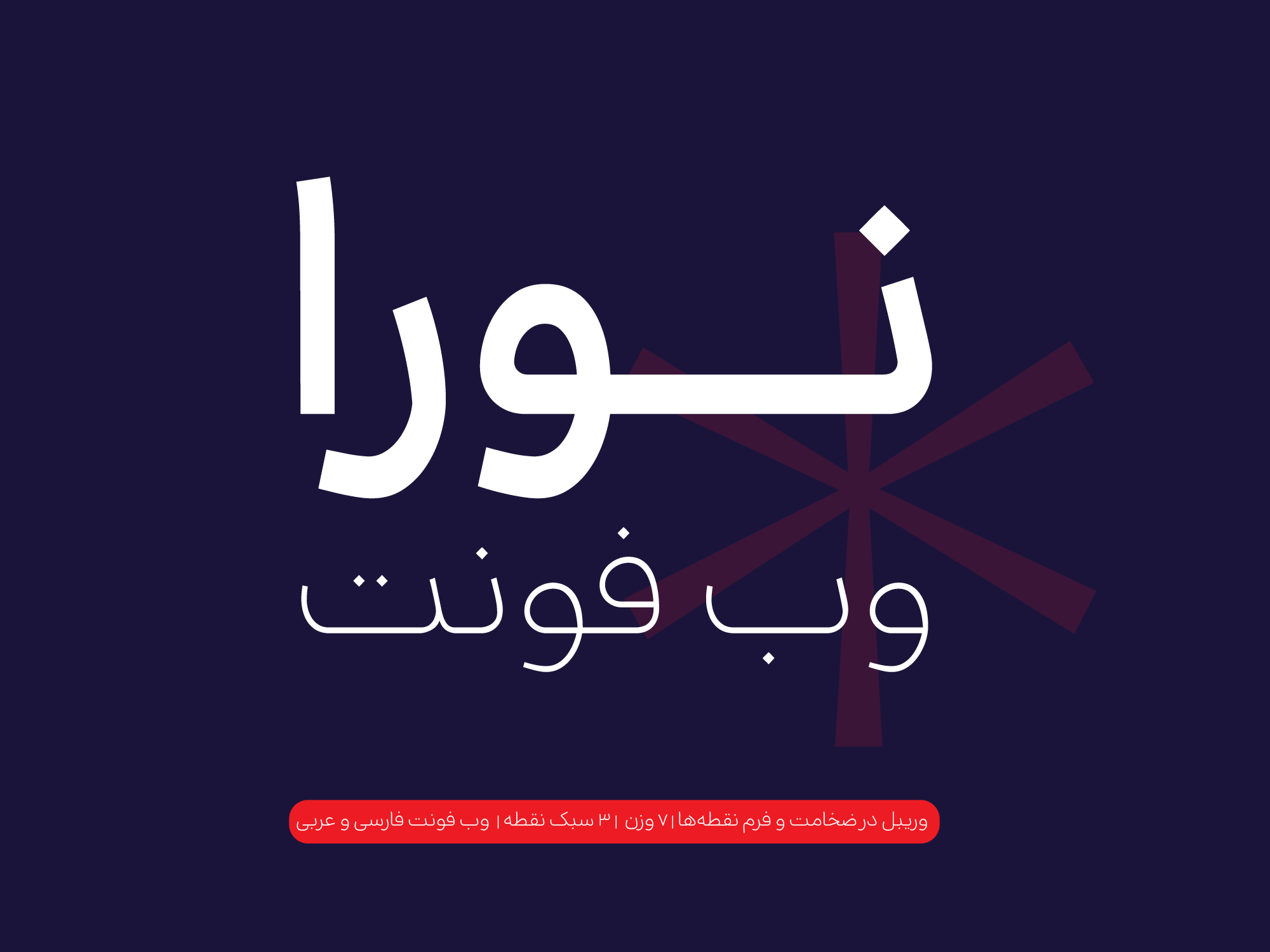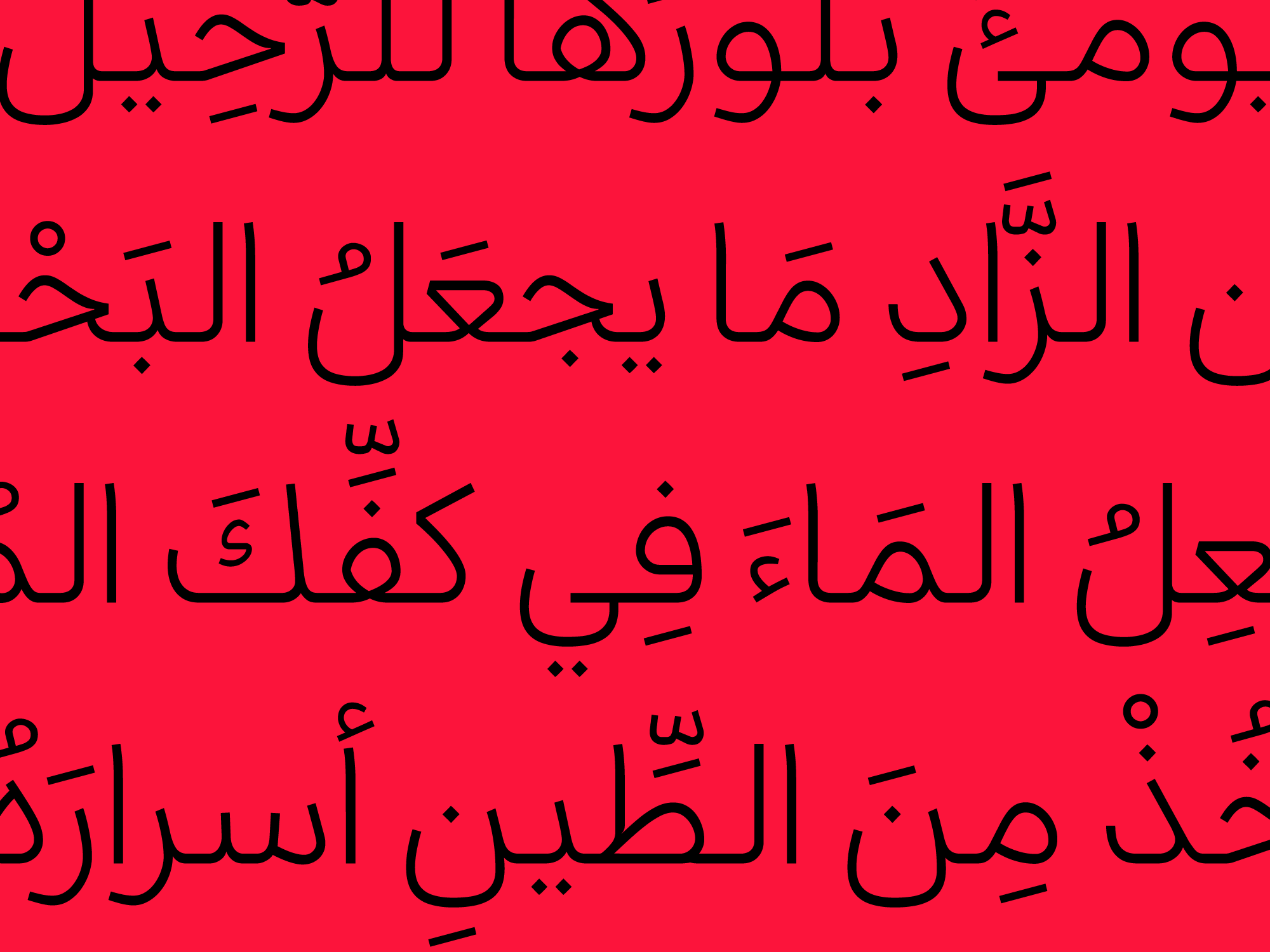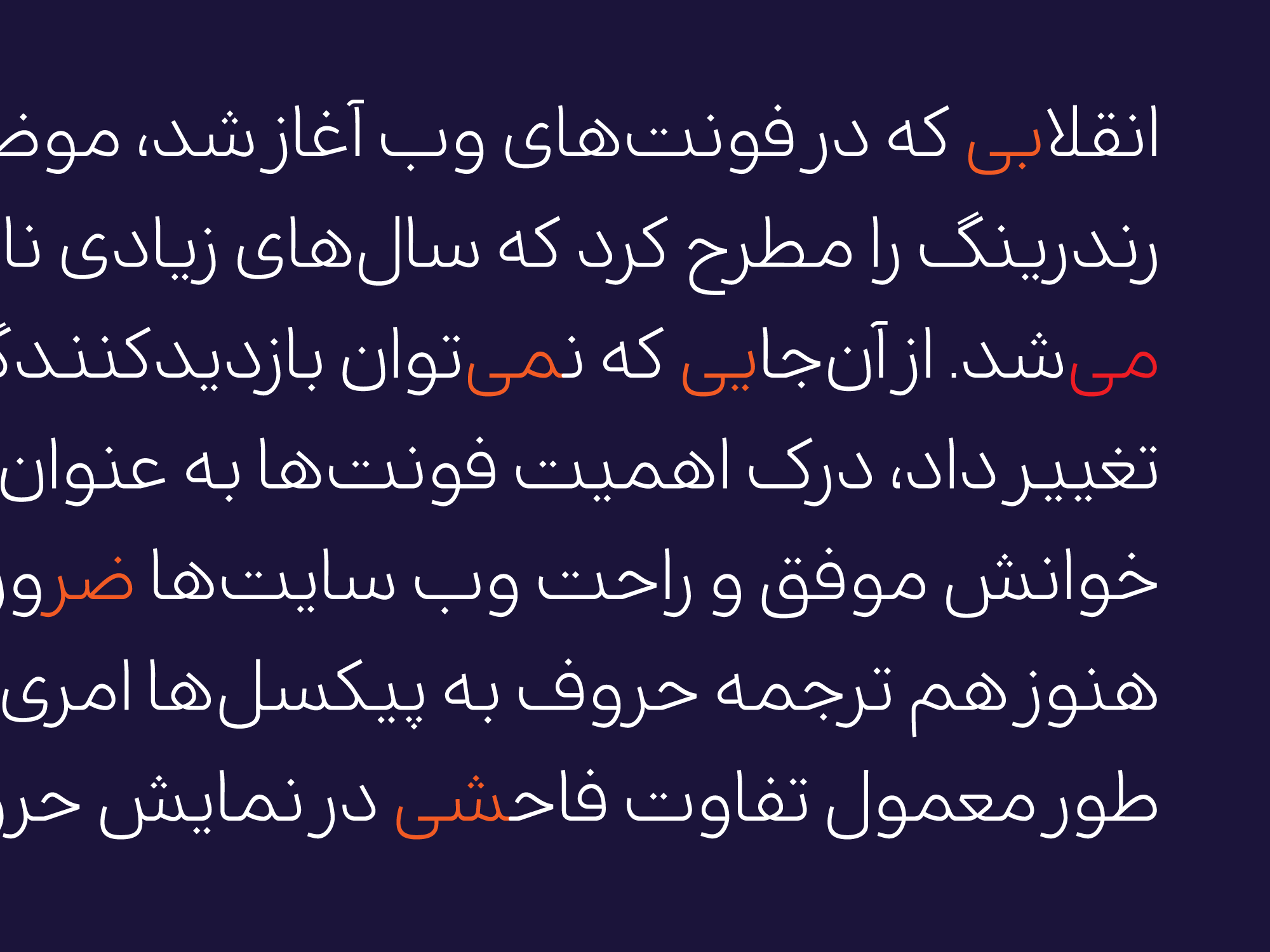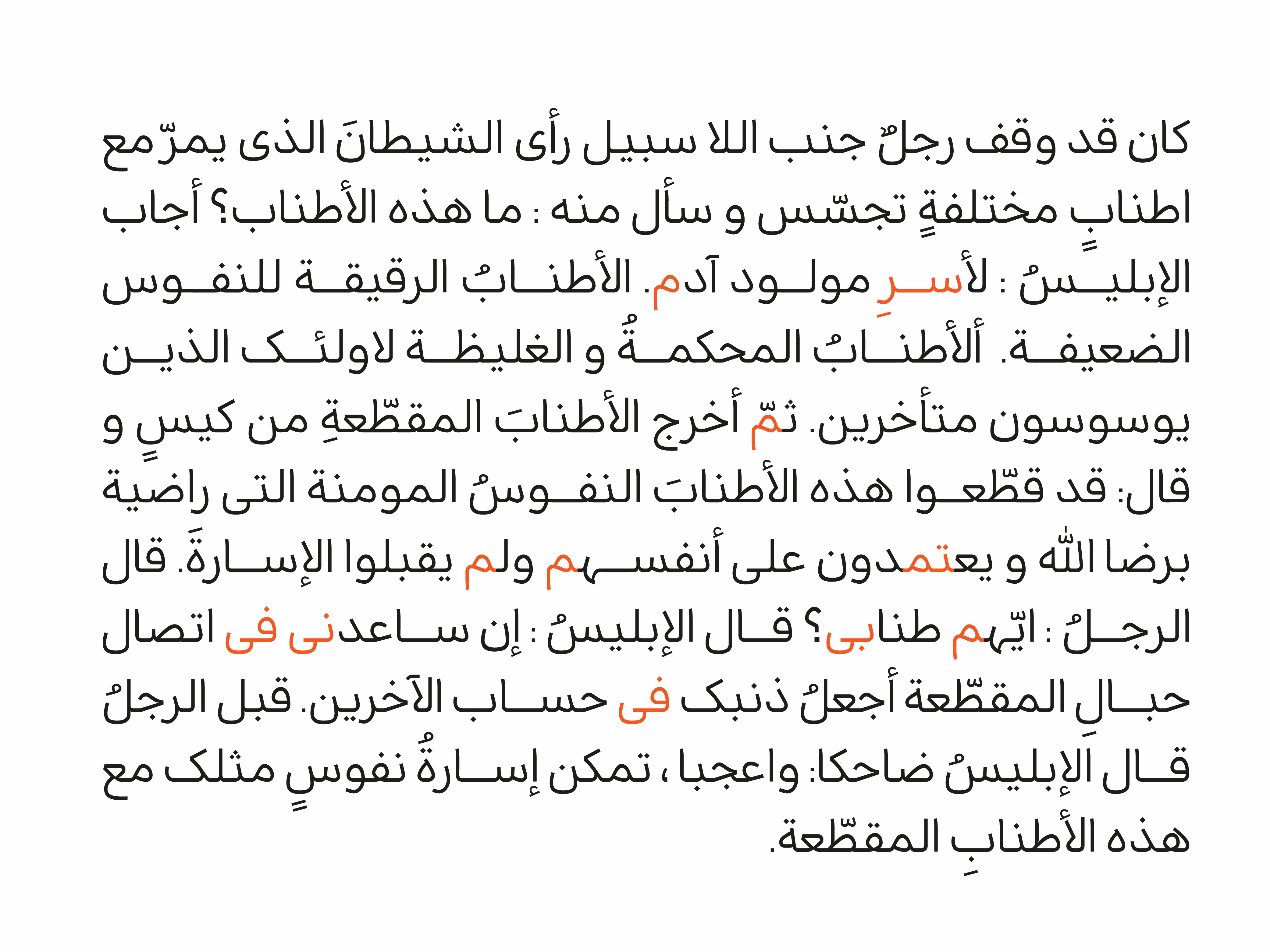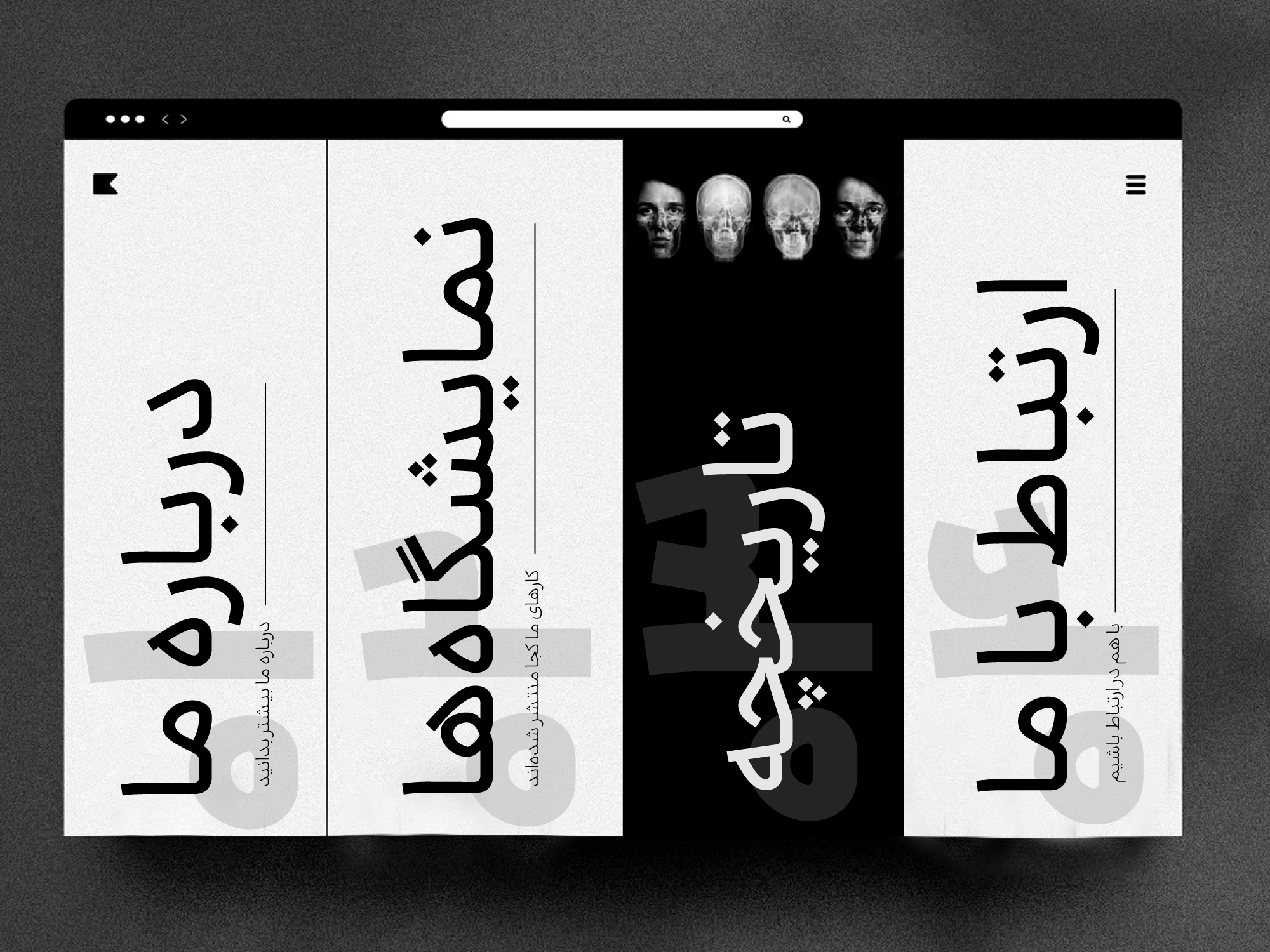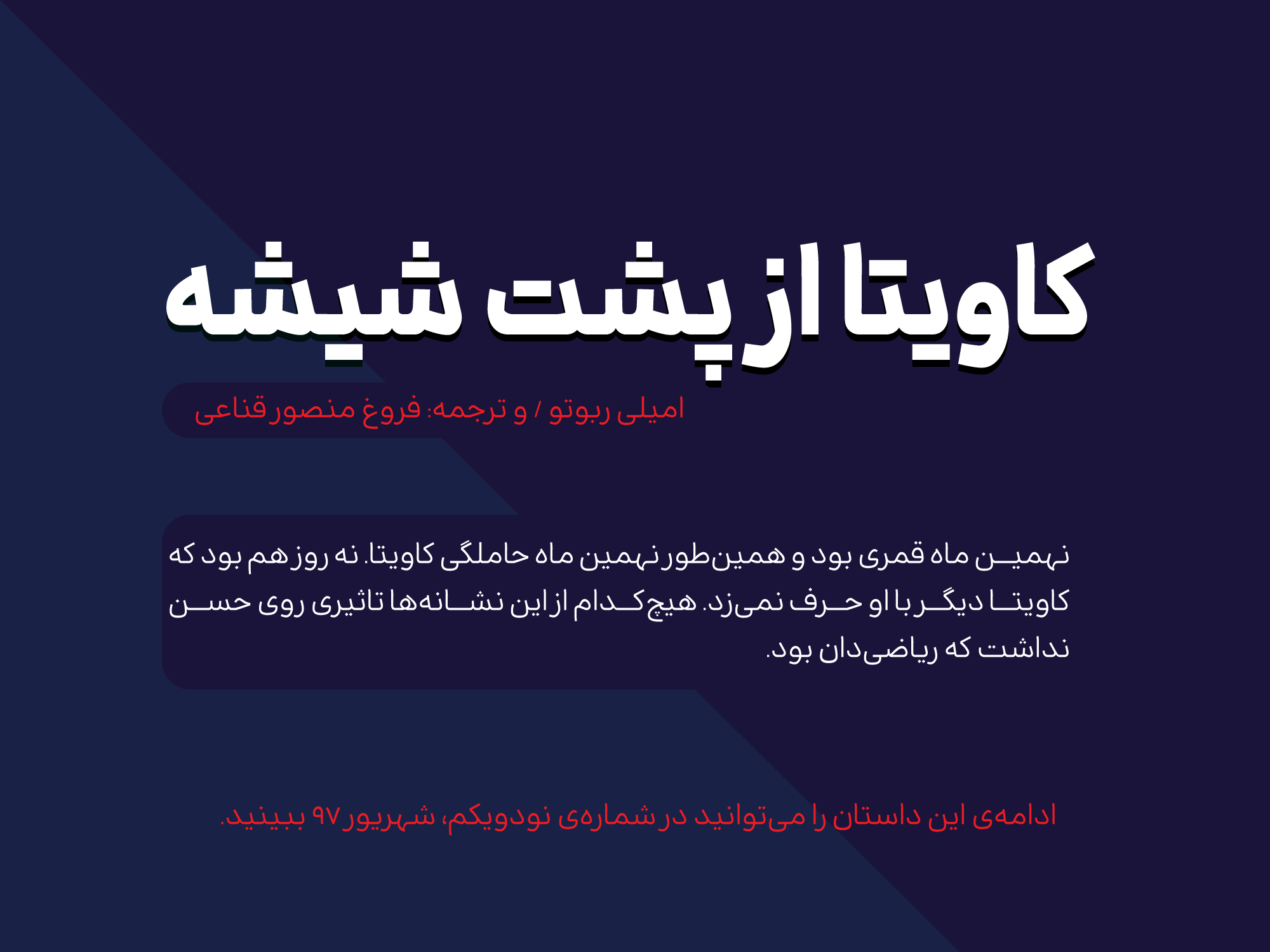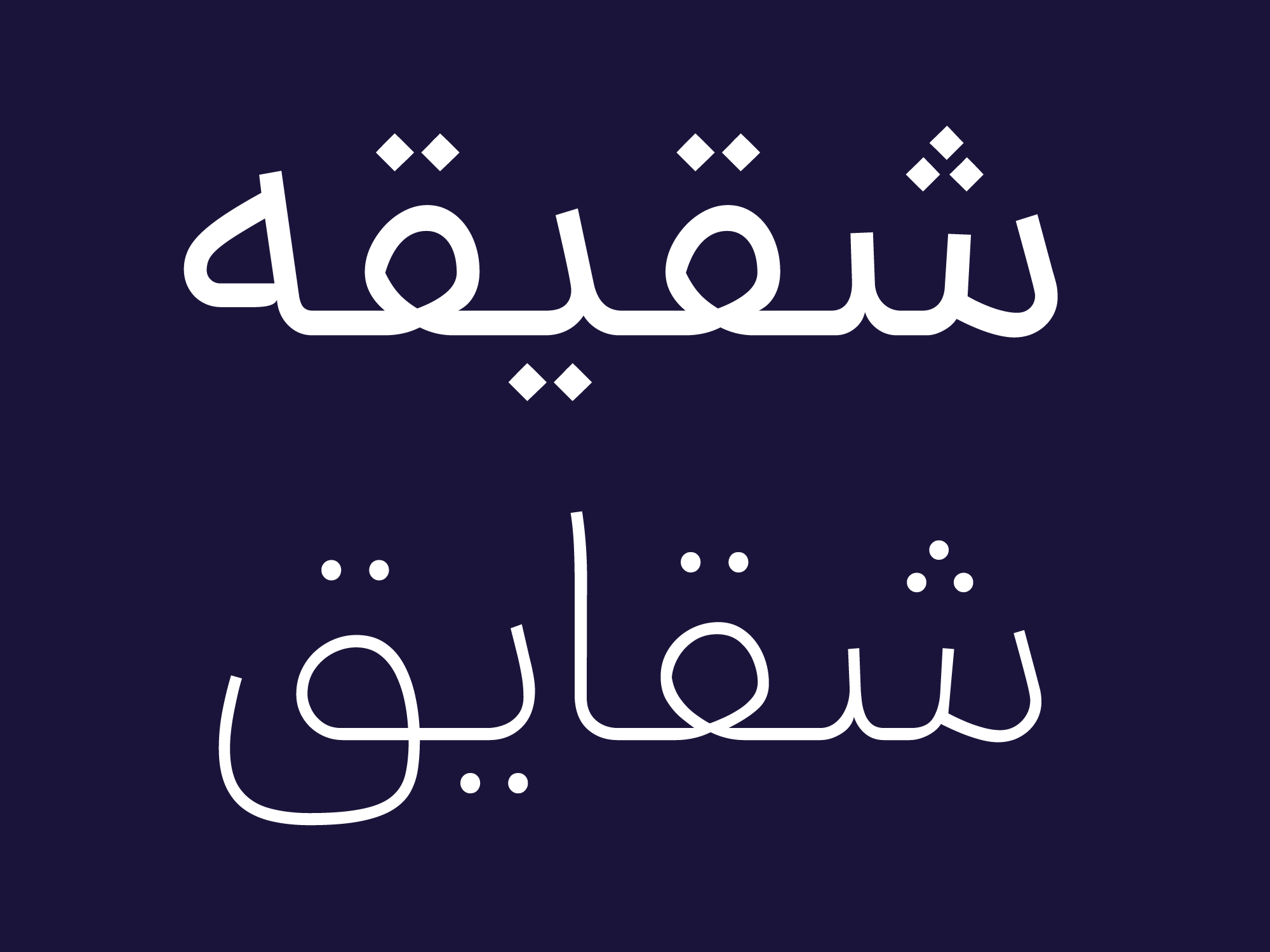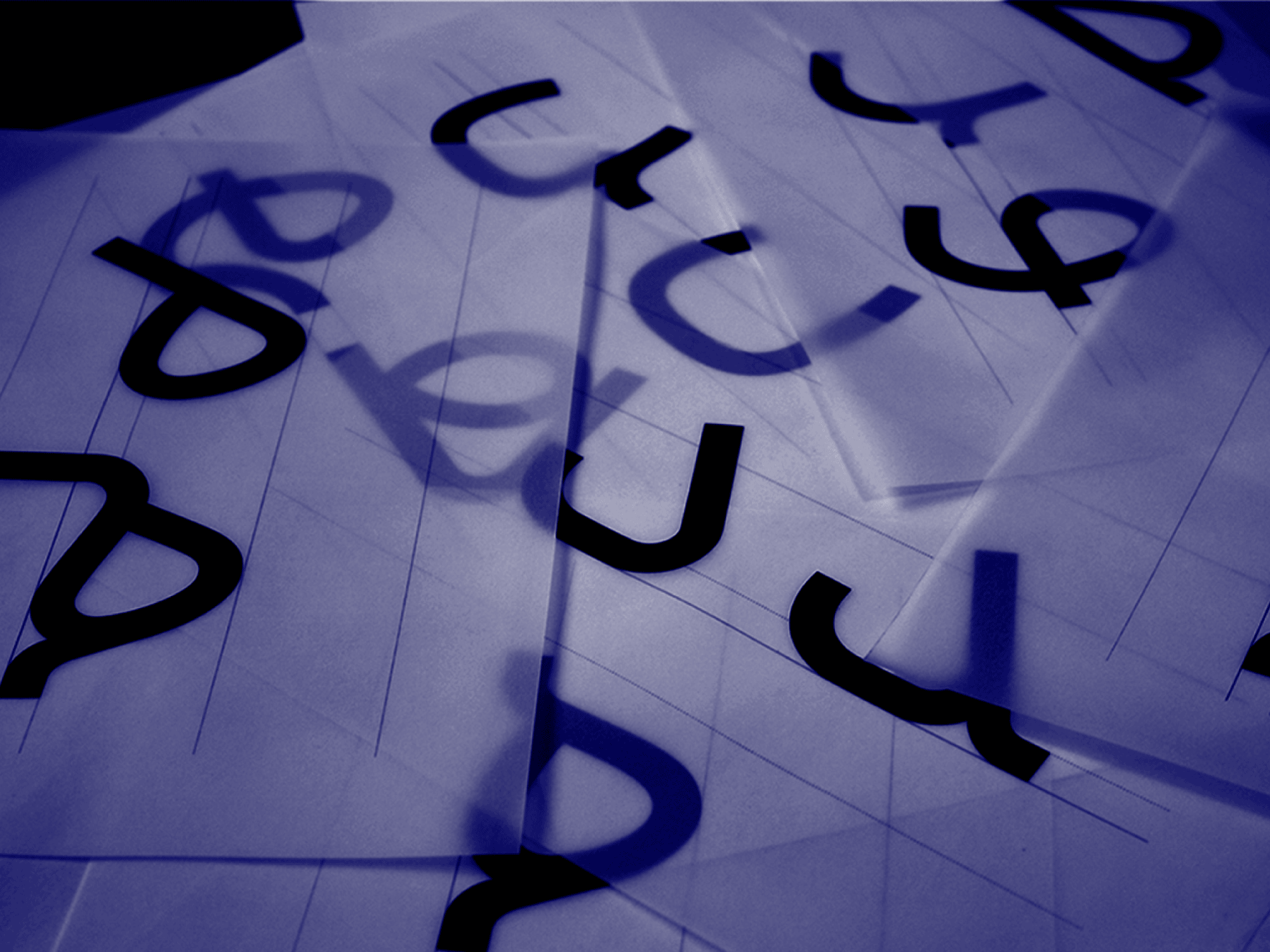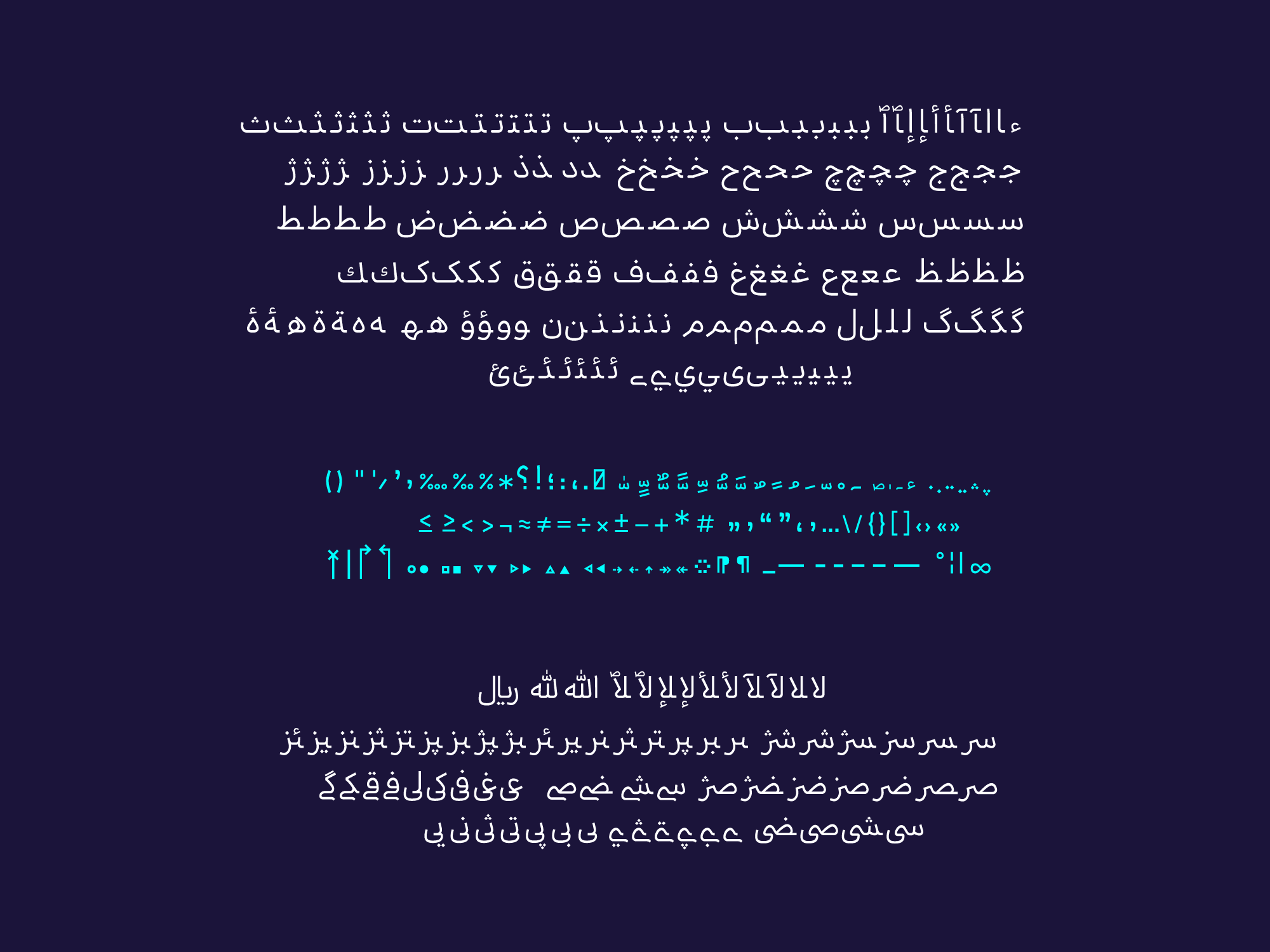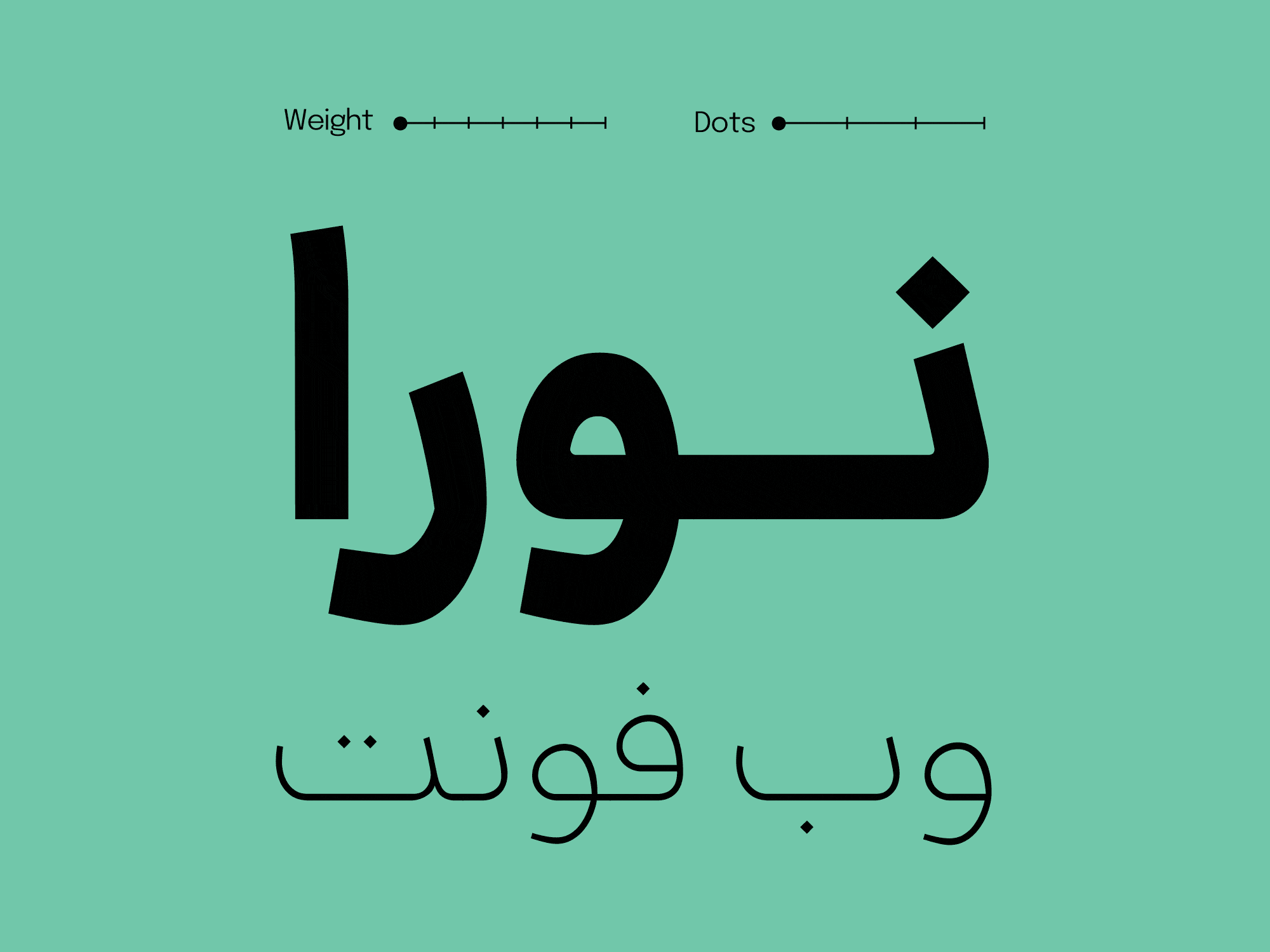
تنوع وزنها در فونت نورا:
خانواده حروف نورا دارای 7 وزن (Extralight, Light, Regular, Medium, Semibold, Bold, Extrabold) است که همگی از نظر سبک طراحی از یک جنس هستند و عوامل تاثیرگذار در سطح خوانایی در تمام وزن ها رعایت شده است. نسخه وریبل این فونت شامل متغیر ضخامت و نقطه است. تغییر در نقطه ها لحن های مختلفی به این فونت می بخشد.